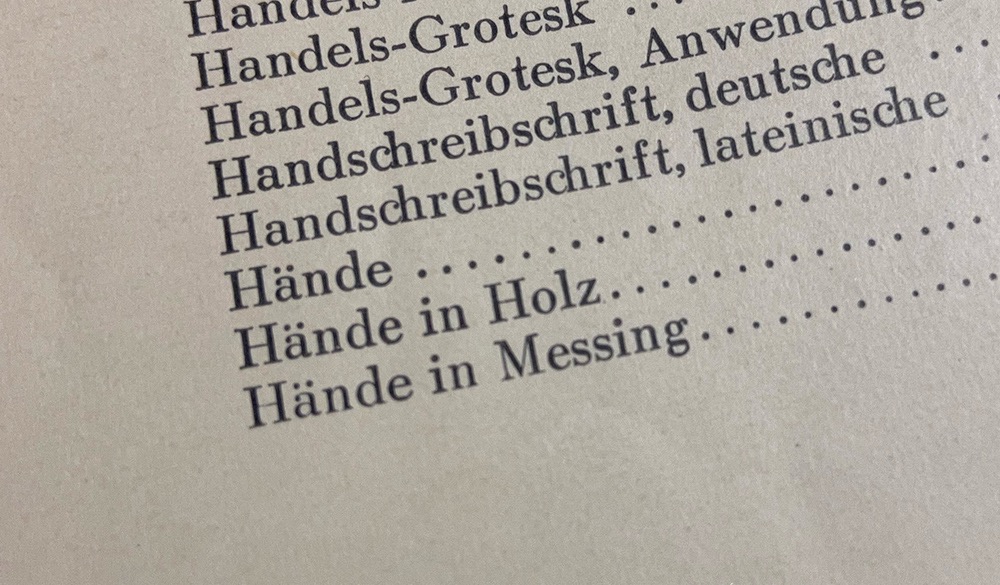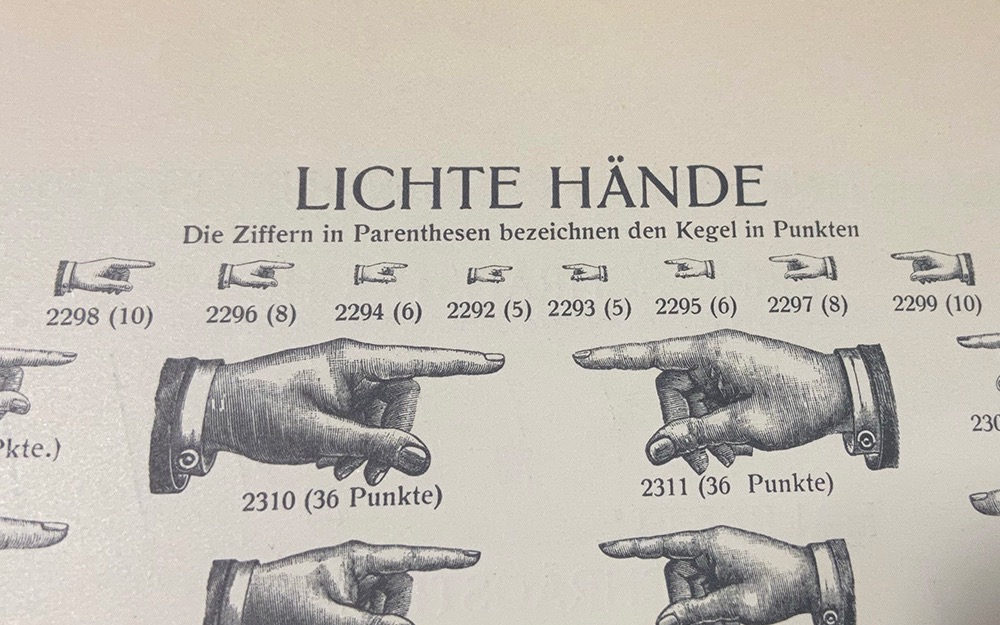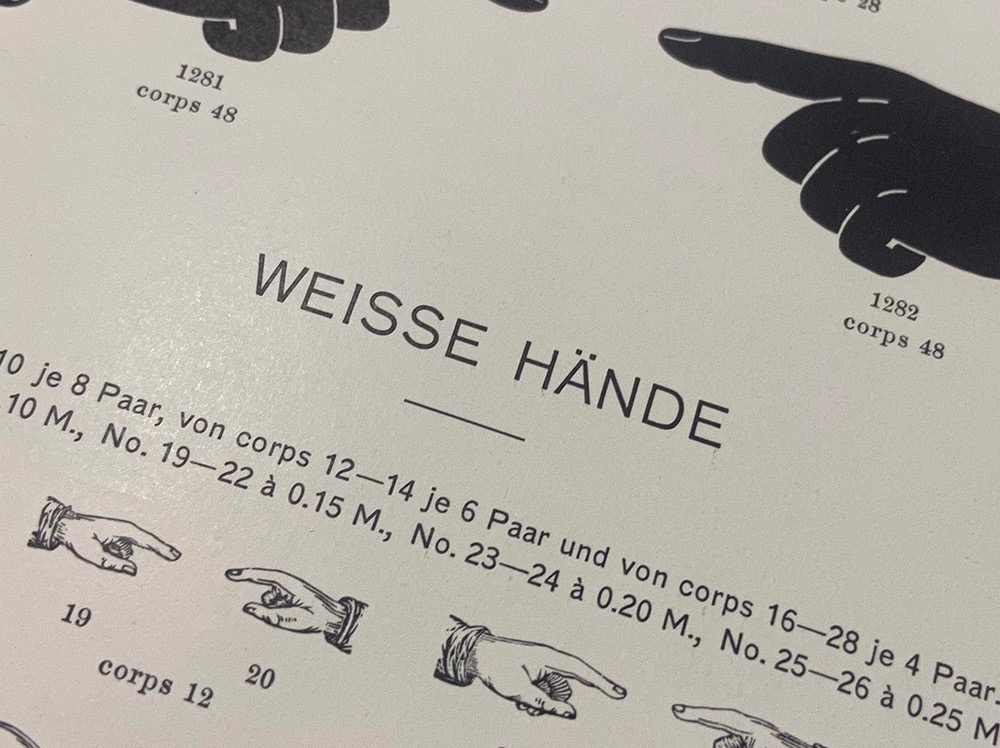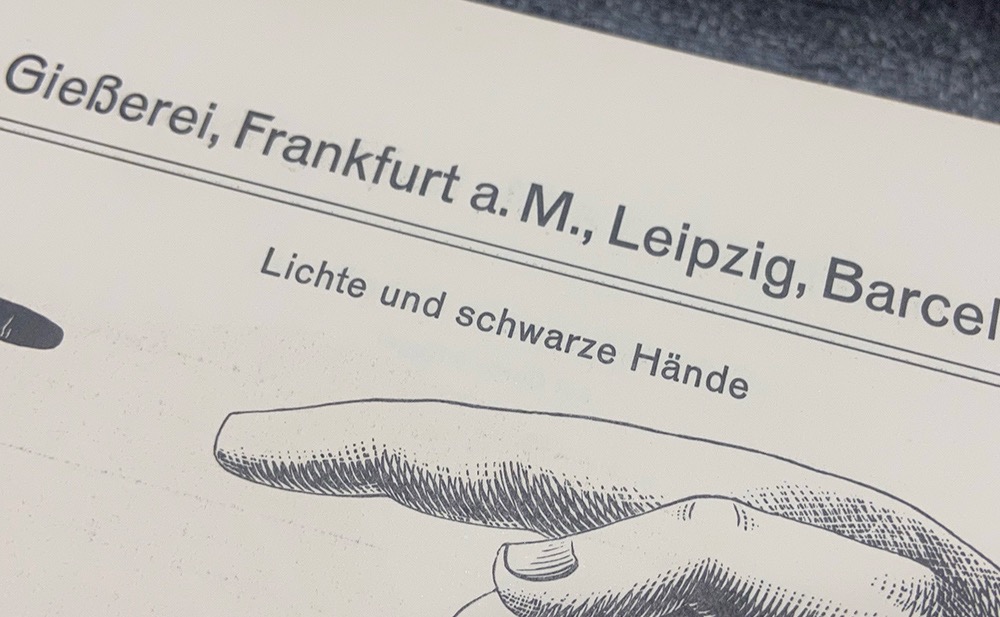
☛ Gibt es eine Bezeichnung für die Hand-Symbole? ☚
Gibt es eine als Wikipedia-Artikeltitel geeignete Bezeichnung für die Hand-Symbole wie ☛ ☚ ☞ ☜ , wie sie beispielsweise in Zeitungsanzeigen Ende 19. / Anfang 20. Hh. üblich waren? Auf Englisch heißen die wohl "manicule" (von lat. maniculum "Händchen") oder gemäß den Unicode-Namen "pointing index" ("zeigender Zeigefinger").
ist eine traditionell übliche Bezeichnung aus der Setzerei. Habe keine Quelle zur Hand, müßte sich aber irgendwo finden lassen.
traditionell übliche Bezeichnung
Und Google hat nicht mal zwei Ergebnis-Seiten?!
Nach dem Überfliegen einiger von Google gefundener Quellen zur Deutehand gibt es für mich eine Verwandtschaft zum Jad.